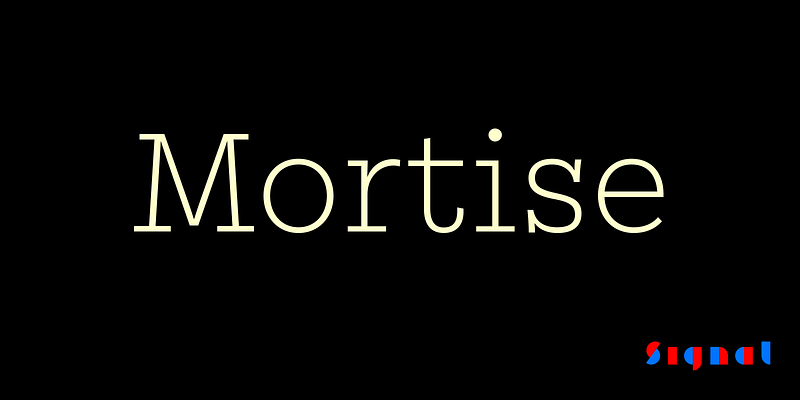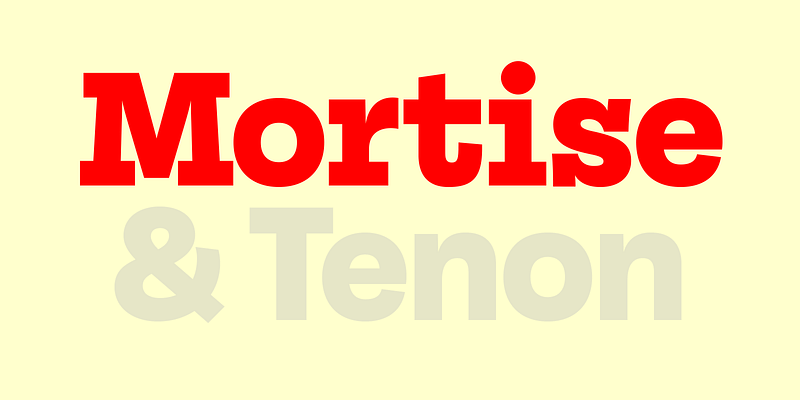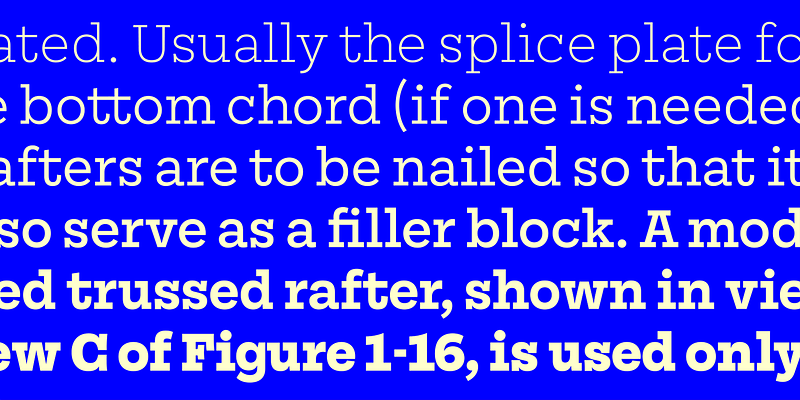
Embutir es “unir o sujetar con seguridad”. Creada por un aspirante a constructor de muebles y un tipógrafo entrado en años, Mortise es una nueva slab serif sólidamente construida. Su generosa altura de x, sus espacios abiertos, sus amplias proporciones y sus trazos de monolínea la hacen legible y práctica, mientras que las largas serifas verticales, ligeramente curvadas, le otorgan un aire de rufián con mostacho curvado.